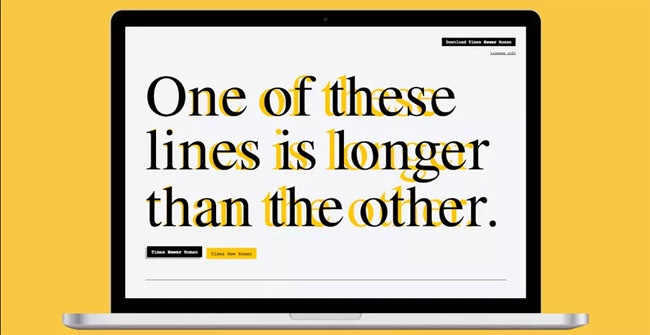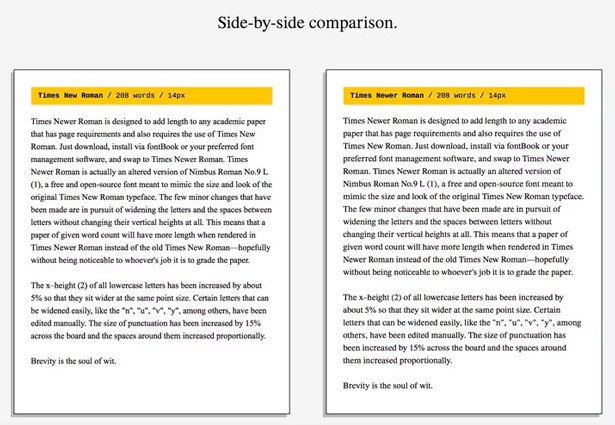
Times Newer Roman là một font chữ do công ty tiếp thị internet MSCHF phát triển. Times Newer Roman sẽ giúp cho mỗi chữ có thể rộng hơn từ 5 đến 10% nhưng trông vẫn không khác gì so với font chữ học thuật nên sẽ giúp cho bài viết của bạn trông dài hơn và đẹp mắt hơn. Với cách này, Times Newer Roman sẽ giúp cho một bài văn với nội dung chỉ khoảng 3 trang sẽ dài như 5 trang trên Windows Office vậy.
Theo trang web của tờ Times Newer Roman, để “phủ” kín 15 trang tài liệu bạn sẽ cần tới 6.680 từ nếu sử dụng font chữ thường, trong khi đó với Times Newer Roman bạn chỉ cần 5.833 mà thôi.
Times Newer Roman được phát triển từ Nimbus Roman No.9 L - một font chữ miễn phí và mã nguồn mở. MSCHF đã phát triển để font chữ Nimbus Roman No.9 L rộng hơn trong khi đó vẫn giữ nguyên chiều cao và dọc.
Ngoài ra, Times Newer Roman chỉ có thể giúp bạn kéo dài số trang của bài viết. Với những bài viết bị giới hạn số lượng từ thì font chữ này hoàn toàn không giúp ích gì được cho bạn cả.